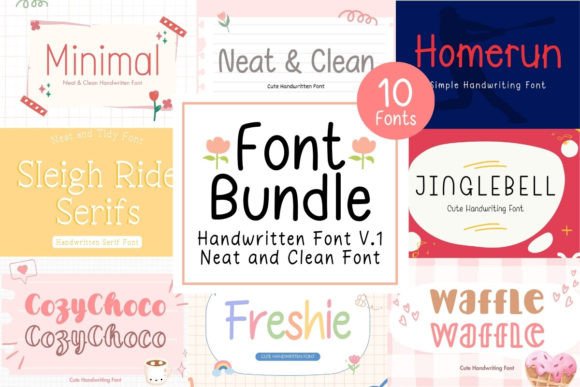
Neat & Clean Handwritten Font Bundle V.1
Si buscas recursos de alta calidad como Neat & Clean Handwritten Font Bundle V.1, este paquete premium es una opción fantástica para tus proyectos creativos.
Elaborado con precisión, Neat & Clean Handwritten Font Bundle V.1 proporciona vectores limpios, tipografía suave y una licencia comercial para tu tranquilidad.
Ya sea que estés creando productos POD (impresión bajo demanda), invitaciones de boda o gráficos para redes sociales, Neat & Clean Handwritten Font Bundle V.1 es una opción ideal.